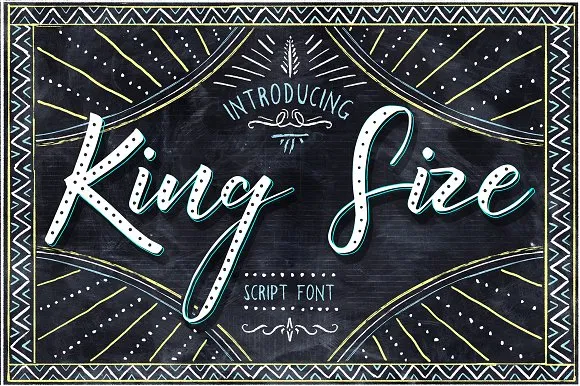
King Size Script Font – Fonte Grátis
King Size Script Font
Introduzimos a King Size Script Font! Desenvolvida por Ivan Rosenberg, esta é uma fonte premium vendida na Creativemarket. Agora, estamos oferecendo-a gratuitamente para download. A King Size é uma fonte elaborada à mão com suporte multilíngue. É perfeita tanto para cabeçalhos quanto para menus de restaurante, cartões de cumprimentos, convites e casamentos. E ela traz todo um conjunto completo de letras minúsculas e maiúsculas, números, alternativas, ligações e suporte multilíngue. Este é o tipo de fonte que pode enriquecer sua marca ou projetos gráficos. Seja para assinaturas profissionais ou design pessoal, a King Size Script oferece uma sensação de elegância que certamente impressionará seus clientes.